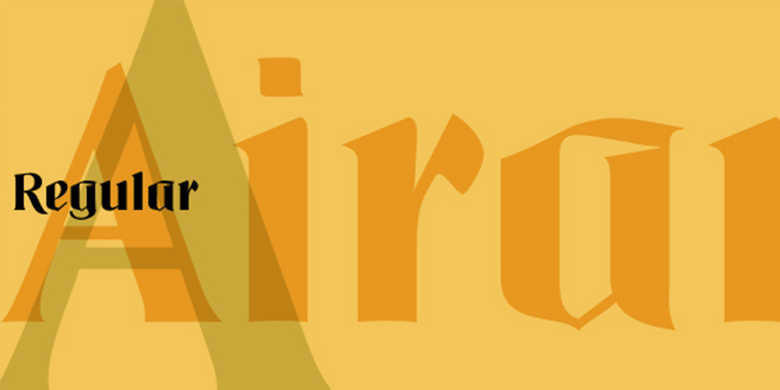
Airam将当代的易读性与历史上的哥特黑体字形式融合在一起,创作了一个与古老的欧洲历史对话的当代文本字体。“哥特黑体”一词指的是一种从北欧中世纪手稿传统演变而来的字体风格。这些字母通常被称为哥特字母,或者古英语,这些字母是通过其形状中宽笔尖笔触痕迹来识别。这种风格的字体通常表现出强烈的粗细笔画对比。它们往往设置得较窄,使整个页面呈现黑色调。而且,这些字母的笔画在自然界中也很不连贯(实际上,德语中的blackletter术语是gebrochene Schriften-字面意思是不连贯的字母)。
为了符合这一要求,当把Airam放在一页纸上时,它的颜色肯定比其他大多数当代文本的颜色要深。Airam的字体也有一些破损。它们显示有角度的关节,而不是平滑的曲线。这个“破碎”的方面实际上有助于在更小尺寸上的易读性。虽然Airam可能不适合整本书或整份报纸的排版,但这种字体会给短小的文本增加一种华丽的感觉。此外,Airam在大标题中看起来非常棒。
Airam于2002年由奥地利设计师Maria Martina Schmidt设计,并被Linotype GmbH收录在Take Type 5家族中。
Airam blends contemporary legibility with historic blackletter forms, creating a contemporary text face that speaks to the old European past. The term blackletter refers to a style of typefaces that evolved out of Northern Europe’s medieval manuscript tradition. Often called gothic, or Old English, these letters are identified by the traces of the wide-nib pen stroke within their forms. Typefaces designed in this style normally exhibit a drastic thick-thin stroke contrast. They tend to be set a bit narrow, leaving the appearance of a black tone across the page. The strokes of these letterforms also appear quite broken" in nature (indeed, the German term for blackletter – gebrochene Schriften – literally means broken letters).
To fit the bill, when set on a page, Airam certainly appears darker than most other contemporary text faces. Airam’s letterforms are slightly broken, too. They display angled joints in lieu of smooth curves. This "broken" aspect actually aids legibility at smaller point sizes. While Airam may not be suitable for setting whole books or newspapers, this font will add a splendid touch to short tracts of small text. Additionally, Airam looks superb in large headlines.
Airam was designed in 2002 by the Austrian designer Maria Martina Schmidt, and is included in the Take Type 5 collection from Linotype GmbH."